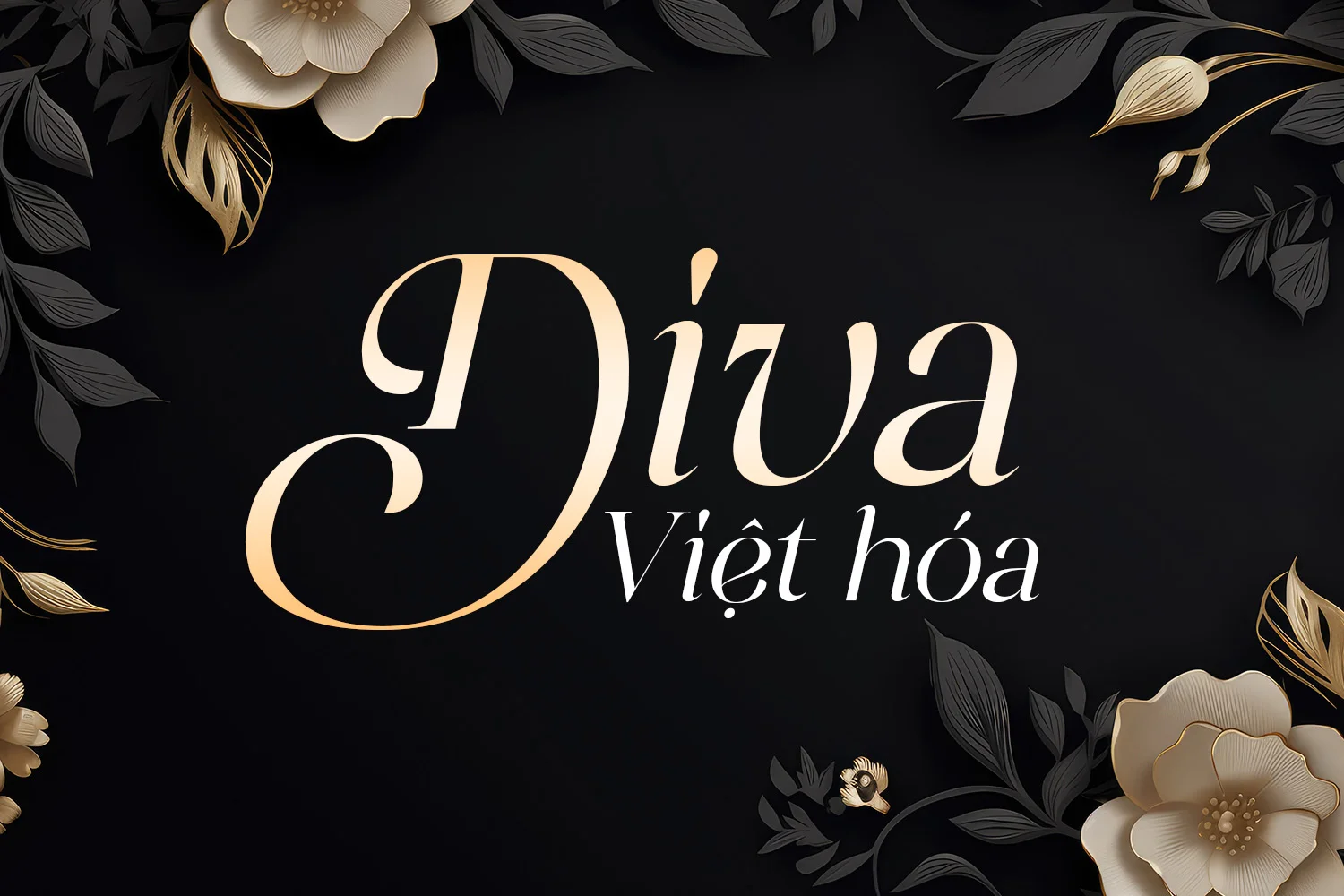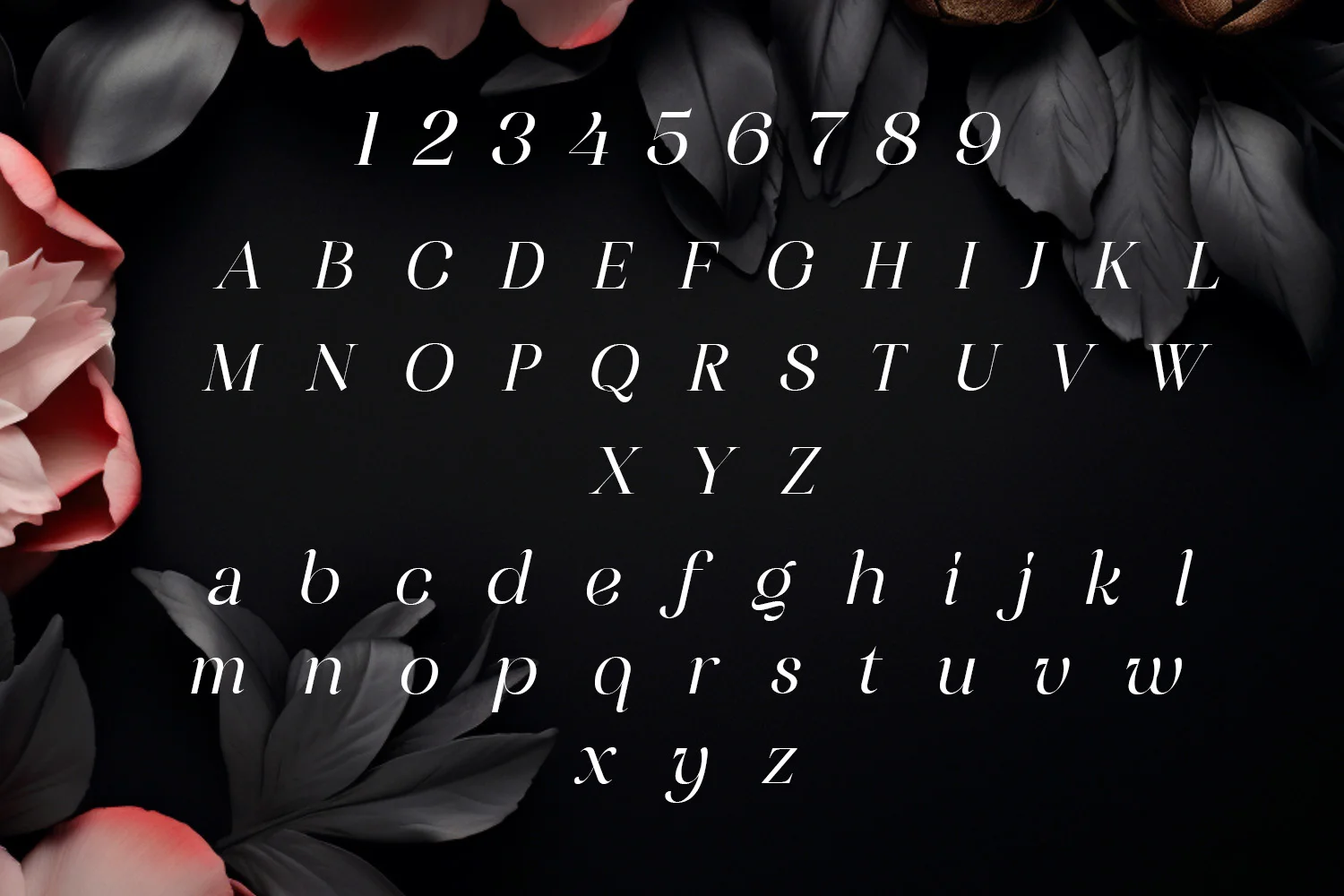
DVN Diva Việt Hóa – Font chữ Thanh lịch, bay bổng và đậm khí chất Diva
DVN Diva Việt Hóa là một kiểu chữ italic serif nghệ thuật mang đậm vẻ đẹp kiêu sa, mềm mại và đầy bản lĩnh, đúng như tên gọi “Diva” – một biểu tượng của sự nổi bật và tinh tế.
Font sở hữu các nét chân thanh đậm hài hòa cùng với đường uốn lượn duyên dáng, mang đến cảm giác bay bổng nhưng vẫn vững chãi và cao cấp. Đây là lựa chọn lý tưởng cho các thiết kế như:
✨ Logo thời trang,
✨ Thiệp cưới cao cấp,
✨ Tiêu đề tạp chí,
✨ Bao bì mỹ phẩm hoặc
✨ Bất kỳ sản phẩm nào hướng đến sự thanh lịch và khác biệt.
Phiên bản Việt hóa được chăm chút kỹ lưỡng, đầy đủ dấu tiếng Việt.